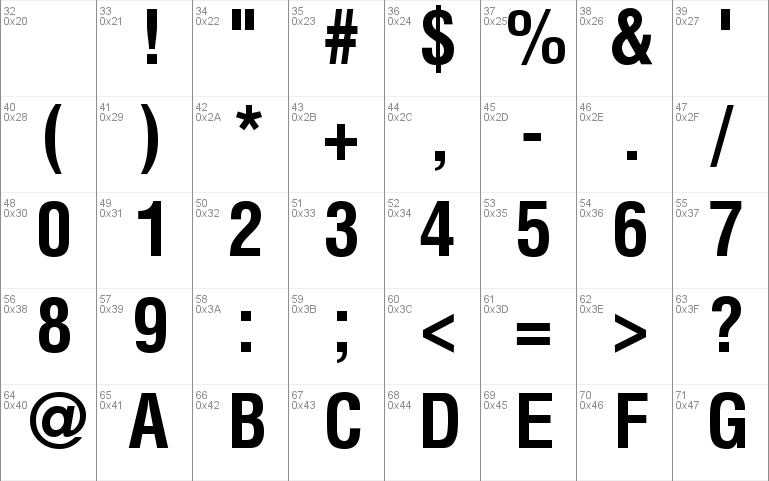
Font VNI Helve Condense Việt Hóa
Phân loại: Cá tính
Kiểu chữ: Sans-serif
Độ dày: Regular
Font VNI Helve Condense
Font VNI Helve Condense Việt Hóa, thuộc bộ font VNI, mang phong cách hiện đại và thanh lịch, lý tưởng cho các dự án thiết kế như thiệp mời, bìa sách, và tài liệu văn phòng. Với các nét chữ không chân và độ dày đều đặn, Font VNI Helve Condense Việt Hóa không chỉ dễ đọc mà còn tạo cảm giác chuyên nghiệp và tinh tế. Việc Việt hóa font giúp người dùng dễ dàng tích hợp vào các thiết kế tiếng Việt, mang lại sự tiện lợi và nâng cao tính thẩm mỹ.